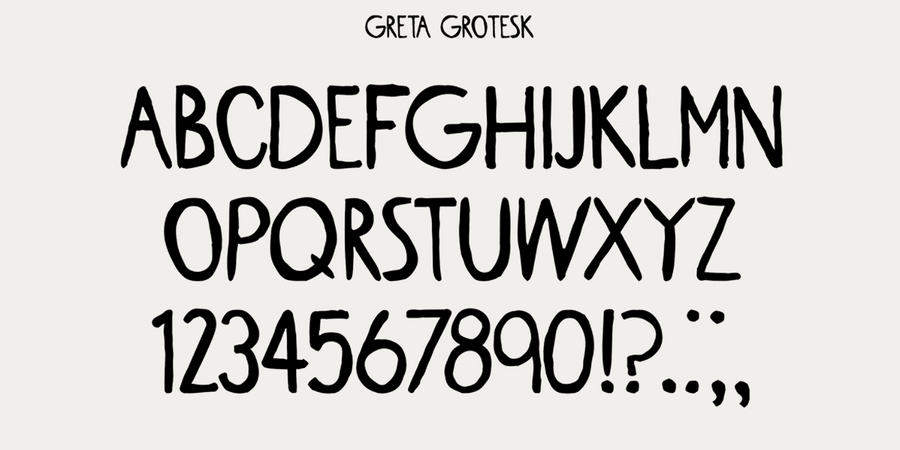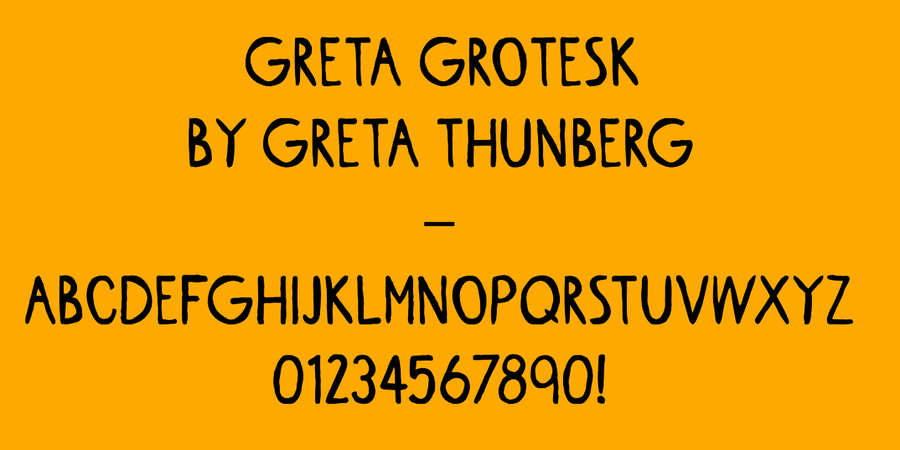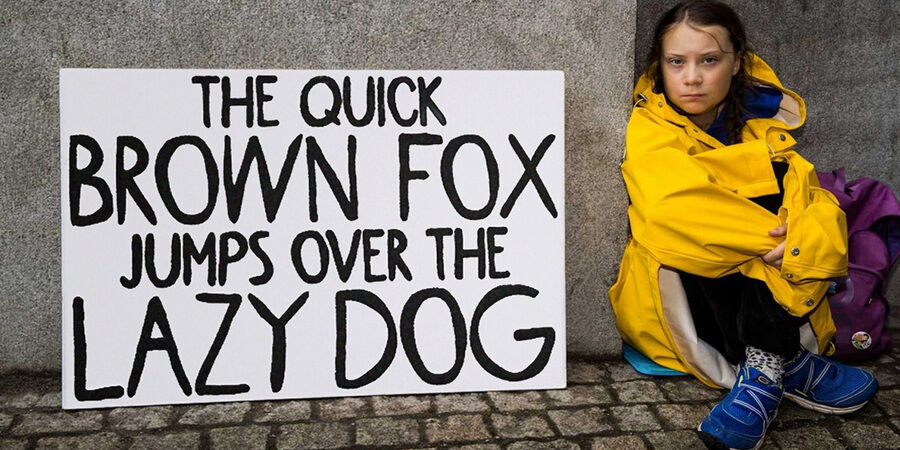
Опис шрифта Greta GroteskҐрета Ґротеск – це шрифт з глобальною місією, зроблений на основі почерку юної екоактівісткі Ґрети Тунберґ. Шрифт безкоштовний для персонального використання. Для комерційного використання, будь ласка, зв'яжіться з правовласником. Автор шрифту каже: «Найбажаніше використання шрифту в дизайні, пов'язаному зі зміною клімату. Але я думаю, що найбільший внесок, який міг би зробити цей шрифт, виходить за рамки необхідності використовувати його в постерах. Шрифти мають цю дивну здатність викликати спогади так само, як почувши пісню, яку давно не чули, ви переноситесь в інший час і місце... Сподіваюся, Грета Гротеск – це ще одна несподівана річ, яка нагадає нам про нагальну проблему і дії, які ми повинні зробити, щоб домогтися реальних змін. Крім того, Greta Grotesk зручно розташований за алфавітом прямо над Helvetica – тож ви не зможете його не помітити ». Шрифт розробив Тал Шуб у 2019 році.
Функції сімейства шрифтів Greta GroteskЗастосування гарнітури у верстці:
Асоціації з сімейством шрифтів Greta GroteskОсобистість і характер гарнітури:
вуличний, побутовий, міський, гучний, сміливий, крафтовий, неформальний, мультяшний, ручний, економний, наївний, рукотворний, кустарний, саморобний, високий, оригінальний, живий, характерний, грайливий, помітний, домашній, виразний, неохайний, ремісничий, потішний, милий, зухвалий, артізанальний, недбалий, кричущий, вернакулярний, свіжий, зрозумілий, ясний, лаконічний, сучасний, модний, приємний, зелений, природний, сімейний, органічний, натуральний, яскравий, знайомий, переконливий, впевнений, політичний, Простий, щільний, мотивуючий, амбітний, добрий, симпатичний, молодіжний, дитячий, шкільний, зимовий, сніжний, динамічний, нервовий
хенд мейд, відпочинок, природа, анімація, мультфільм, закуска, фаст фуд, торгівля, крамниця, базар, школа, щоденник, зошит, Місто, графіті, гумор, котики, дієта, кіно, відео, екологія, родина, селфі, Хюґе, дерево, страйк, Протест, прапор, мітинг, політика, дитяча книжка, море, зима, Інстаграм, графіка, ілюстрація, школяр, школярка, дім, небо, акварель, побут Гарнітура асоціюється з віком: